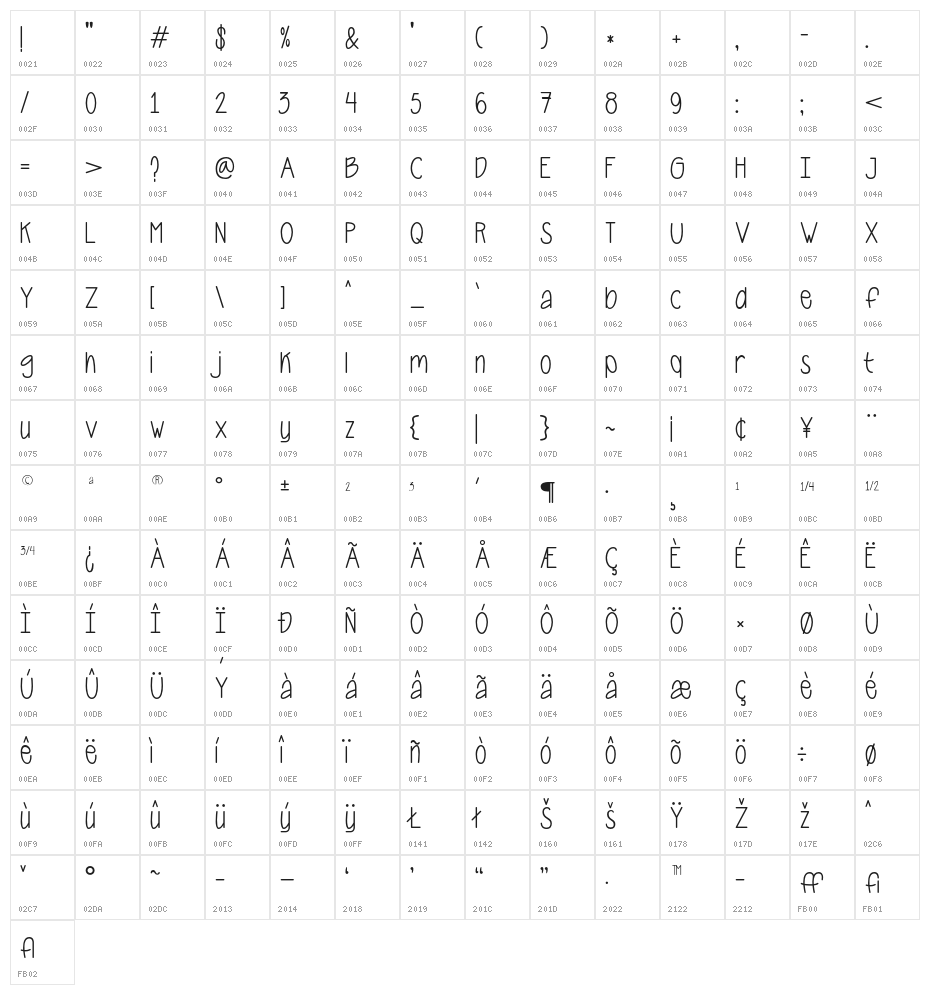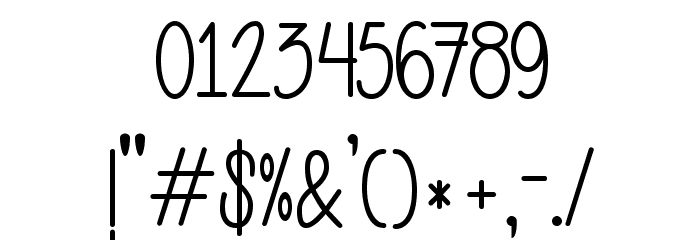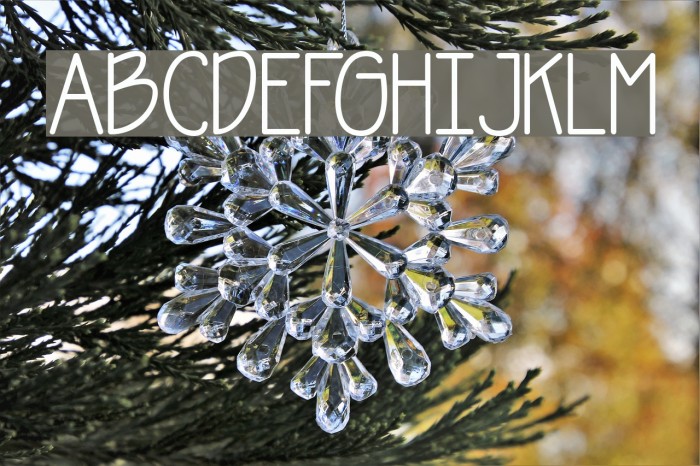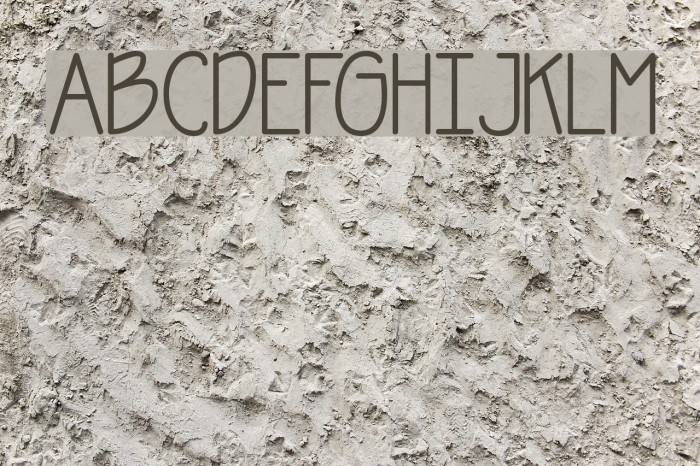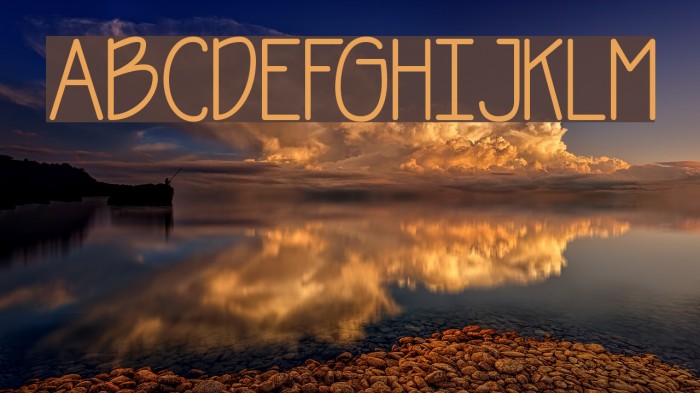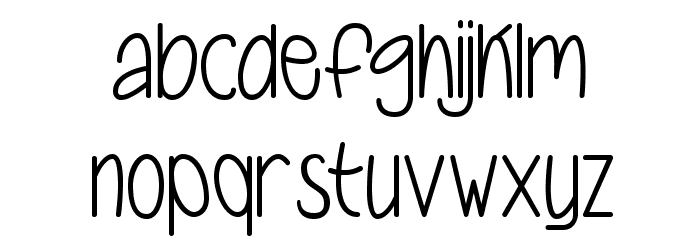
Carnala Font
| Estilo general | Playful |
| Caso de uso | Headlines, Logos, Invitations |
| Proyectos propuestos | Ideal for children's books, greeting cards, playful branding, and casual invitations. |